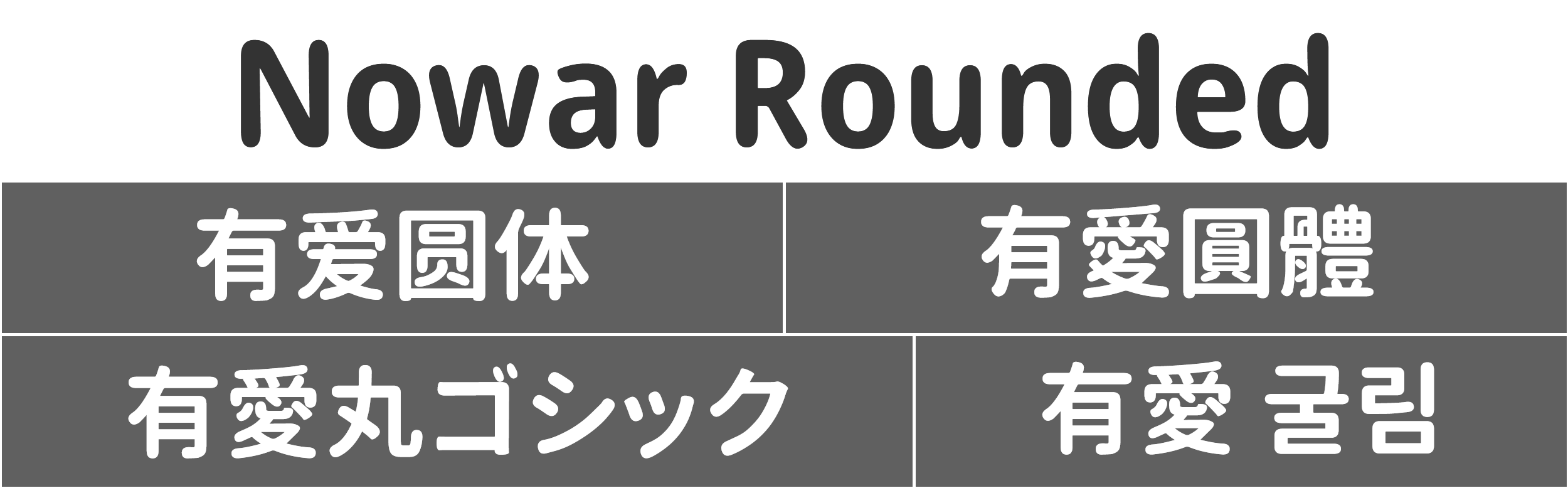
有愛圓體是《魔獸世界》和《魔獸世界:經典版》字型包,支援所有語言。有愛圓體是 Noto Sans 和 Resource Han Rounded 的合併字型。
有愛圓體有 4 種字重和 5 種地區變體,此外還有若干特徵。
字重
300:細體
400:常規
500:中等
700:粗體
地區變體
Bliz 和 Neut 是「標準變體」,遵循各地區的字形標準。
| 西文和韓國語 | 簡體中文 | 繁體中文 | 備注 | |
|---|---|---|---|---|
| Bliz | 中國大陸字形(UI) | 中國大陸字形 | 臺灣字形 | 遵從《魔獸世界》預設字型設定。 |
| Neut | 傳統字形(UI) | 中國大陸字形 | 臺灣字形 | 未指定字形標準時,採用傳統字形。 |
CL 是「傳統變體」,採用傳統印刷字形(即康熙字形)。
| 西文和韓國語 | 中文 | |
|---|---|---|
| CL | 傳統字形(UI) | 傳統字形 |
PSimp、PSimpChat 是針對繁體中文的變體,把繁體字重對映為簡化字字形。
| 通用字型 | 繁體中文文本、戰鬥、提示訊息字型 | 繁體中文聊天字型 | 西文、簡體中文、韓國語 | |
|---|---|---|---|---|
| PSimp | 中國大陸字形(UI,重對映) | 中國大陸字形(重對映) | 中國大陸字形 | 不適用 |
| PSimpChat | 中國大陸字形(UI,重對映) | 中國大陸字形(重對映) | 不適用 |
西文:英語、西班牙語(拉丁美洲)、葡萄牙語、德語、西班牙語(歐洲)、法語、義大利語、俄語。
UI:中西文共用的標點視作西文標點;半形 CJK 標點。
通用字型:
FRIZQT__和ARIALN。某些插件硬編碼了此字型。
特徵
| 標記 | 名稱 | 簡介 |
|---|---|---|
| OSF | Oldstyle | 不齊線、不等寬的舊樣式數字。 |
| SC | Smallcaps | 小型大寫拉丁字母。 |
| RP | Roleplaying | 丶(U+4E36)重對映為 ·(U+00B7,MIDDLE DOT;或 U+2027,HYPHENATION POINT)。 |
預編譯的特徵變體:Bliz,OSF、Bliz,RP、Bliz,SC。